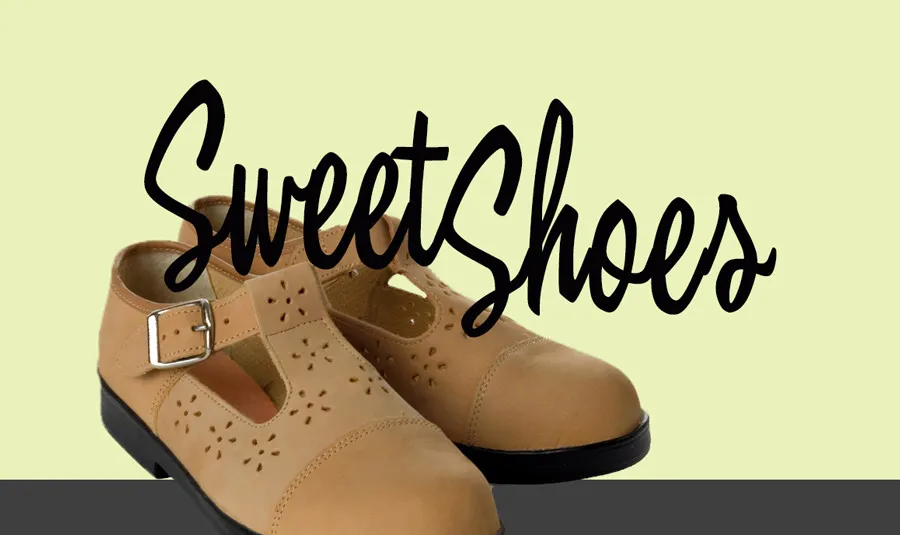
Brown Bag Font – Fonte Grátis
Brown Bag Font
A Brown Bag é uma fonte escrita com traços de pincel que transmite sofisticação natural. Esta bela fonte de mão livre é perfeita para aplicações onde deseja destacar a sua mensagem, como desenho de etiquetas de camiseta ou criação de logotipos. Ainda não experimentou o charme elegante e delicado dessa fonte? É hora de mergulhar nela. Ideal tanto para projetos pessoais quanto para uso profissional, esta fonte oferece uma sensação única que torna-a um excelente complemento para qualquer tipo de design. Não perca a oportunidade de adicionar esse detalhe diferenciador à sua próxima criação visual.